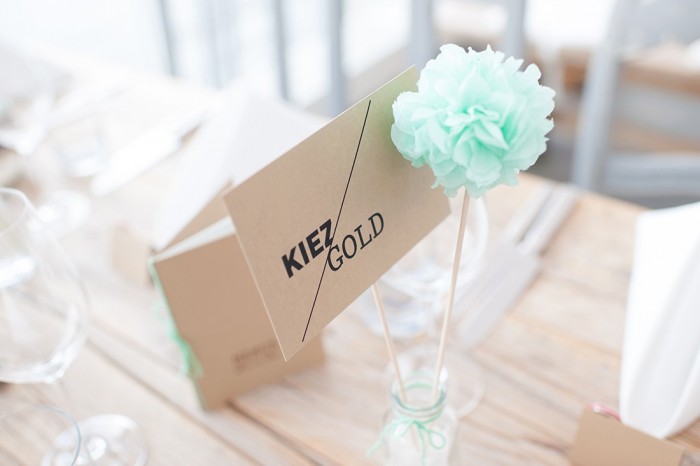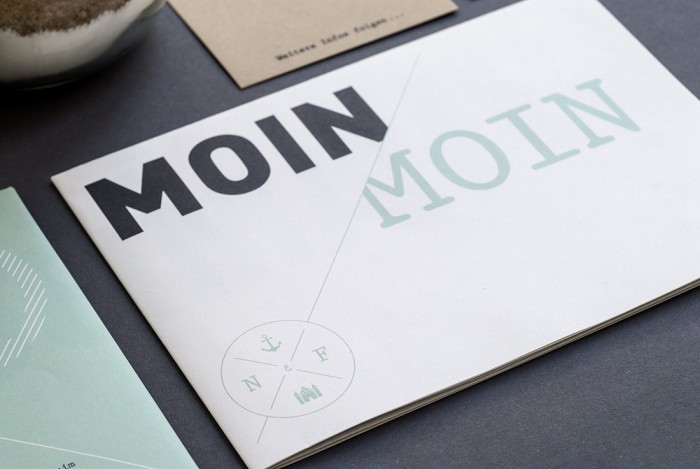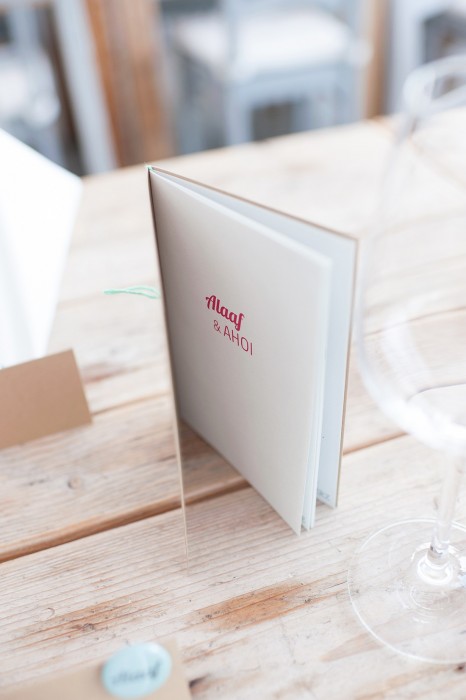
Moin (die Grotesk) sieht nach einer fetten DIN aus, für das andere Moin kannst du mal einen Blick auf Bitter und Copse werfen (die sind es jedoch nicht). Alaaf müsste die Lobster sein.